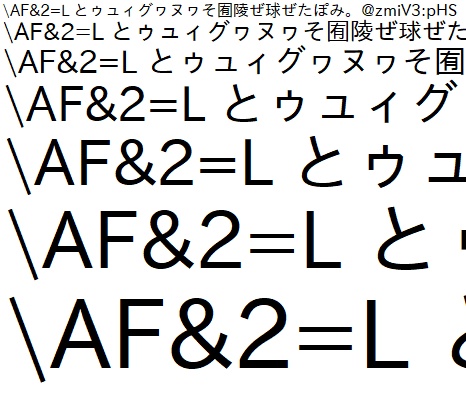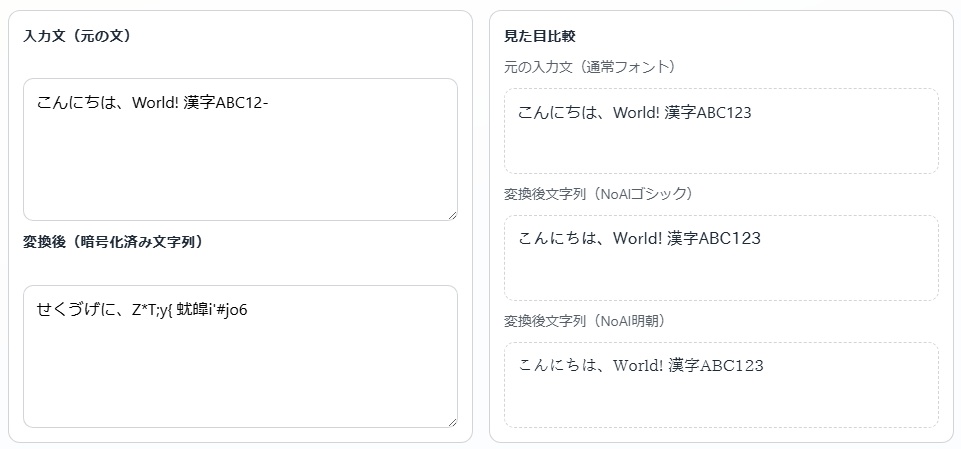
【AIには読めない無料フォント】NoAIFont
AIの無断学習対策に対抗するための暗号化フォントです。 このフォントで書かれた文章は、AIへの入力やプログラムでの読み込み、コピー&ペーストをした瞬間に意味のない文章に変化します。 ※使いかた 1. 同梱のnoai-gothic.ttf(ゴシック体)またはnoai-mincho.ttf(明朝体)をインストールします。(Windowsの場合ダブルクリックしてインストールボタンを押すだけです) 2. 変換したい文章を同梱の変換ツール(converter.html)で変換し、暗号文をNoAIGothicまたはNoAIMinchoというフォントで表示させます。 ※利用規約 【重要】 本フォントはIPAexフォントをベースとするため、「IPAフォントライセンスv1.0」を継承します。本フォントを使用し、複製し、または頒布する行為、その他、「IPAフォントライセンスv1.0」に定める権利の利用を行った場合、受領者は「IPAフォントライセンスv1.0」に同意したものと見なします。 ライセンスの詳細については同梱されている「IPA_Font_License_Agreement_v1.0」、または https://moji.or.jp/ipafont/license/ を参照してください。 上記のライセンスを守る限り、以下の事が可能です。 * 商用・非商用、アナログ・デジタル問わず利用可能です * クレジット表記・利用報告は不要です ※免責事項 * 本フォントはAI学習の完全な防止を保証するものではありません * 本フォントの利用によって発生したいかなる損害・トラブルについても提供者は責任を負いかねます